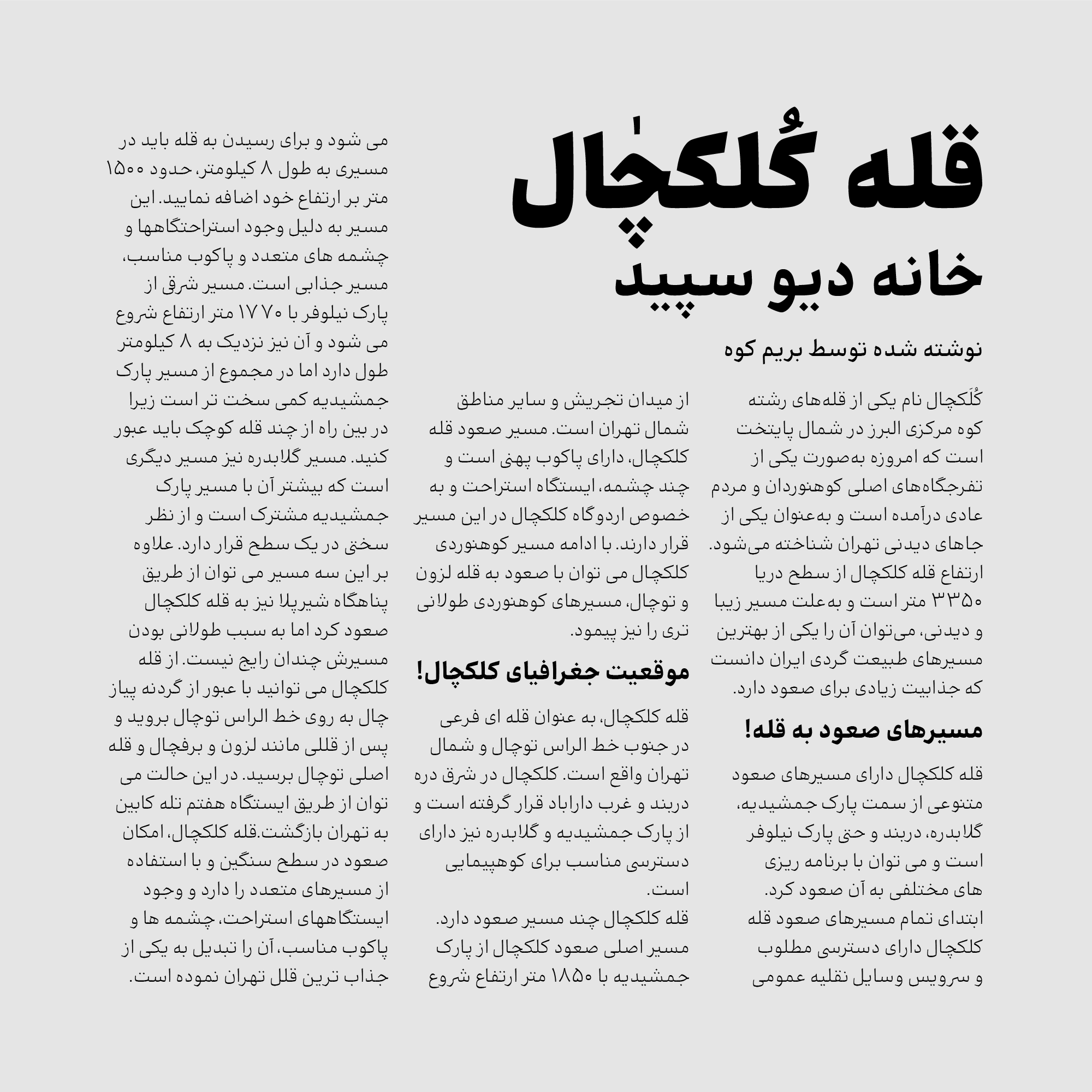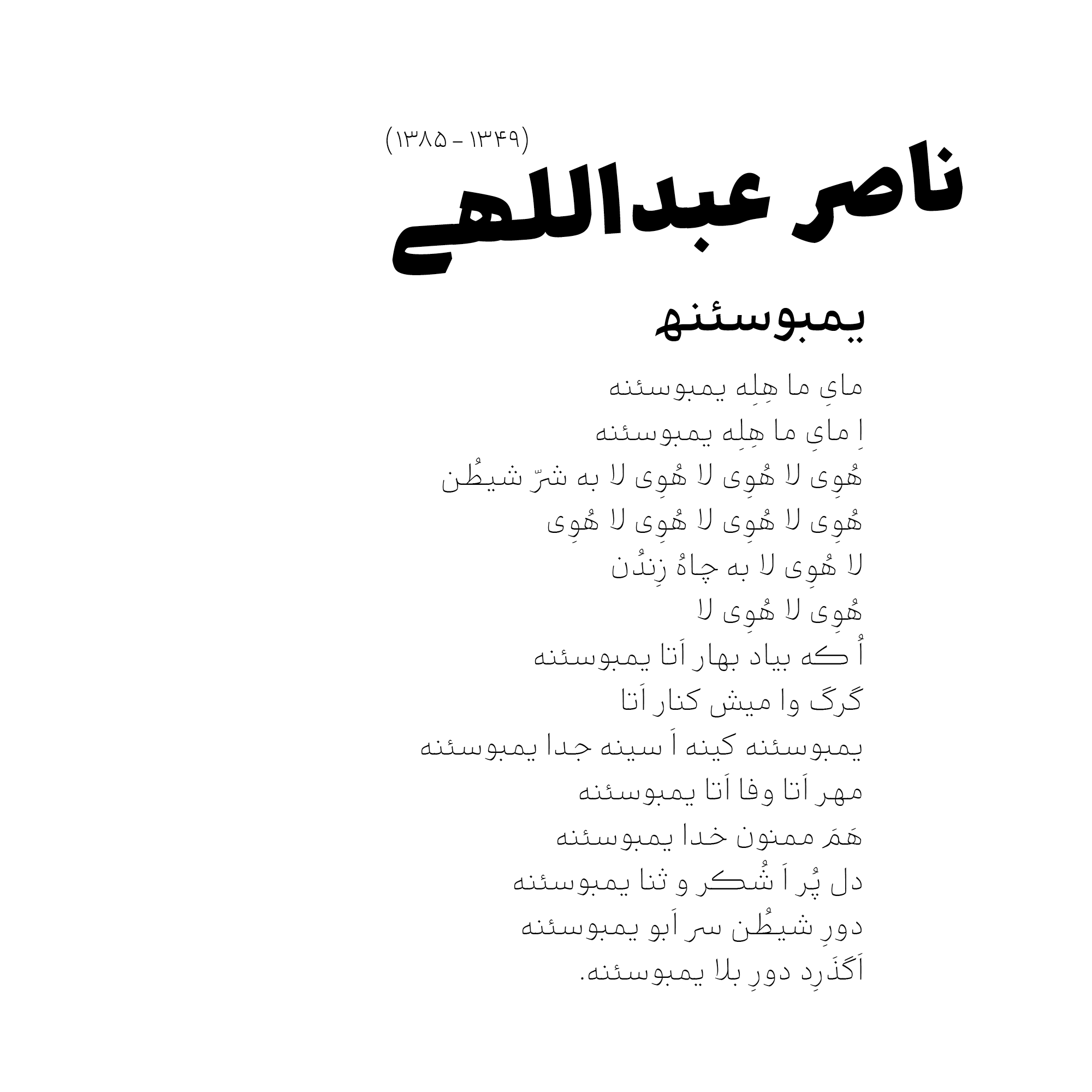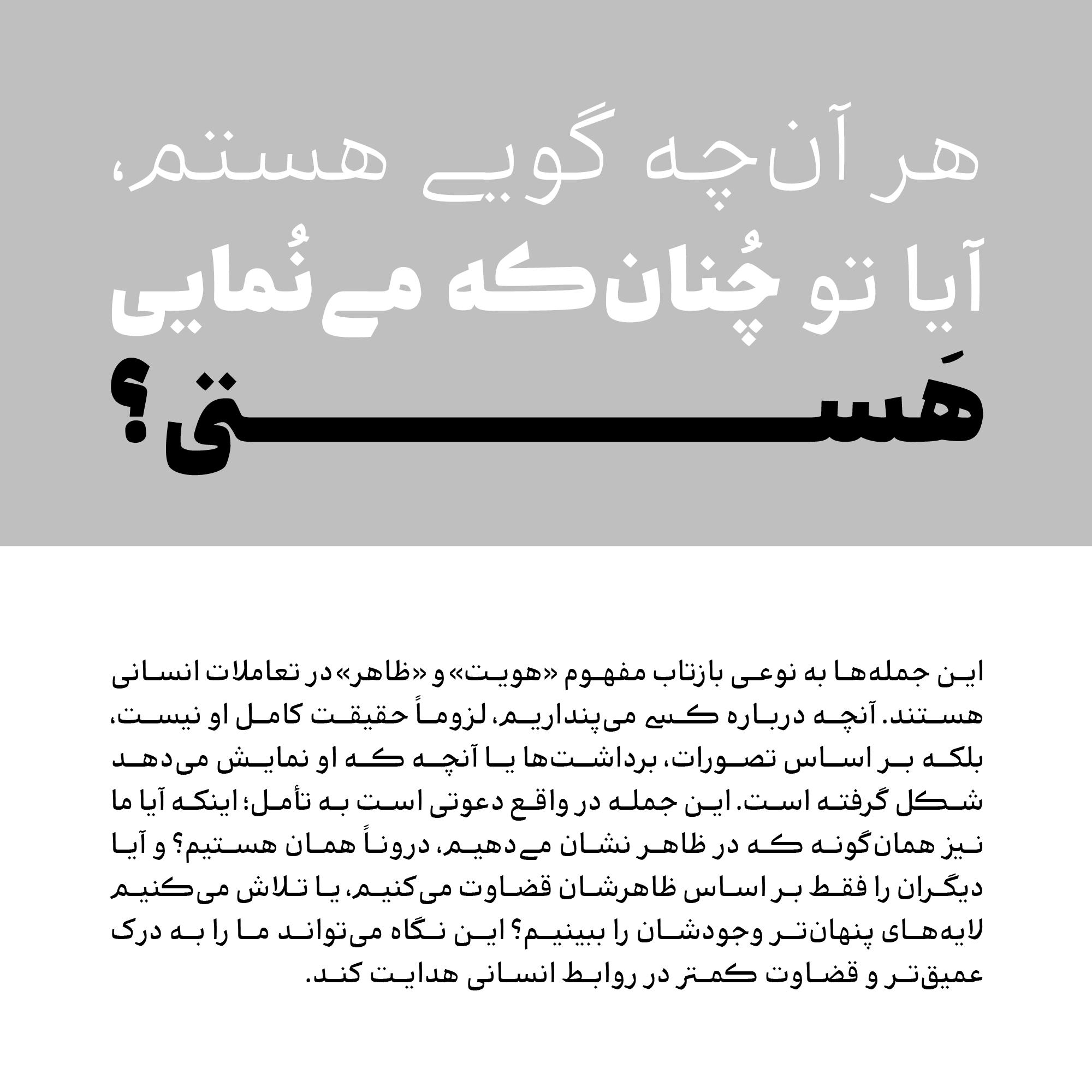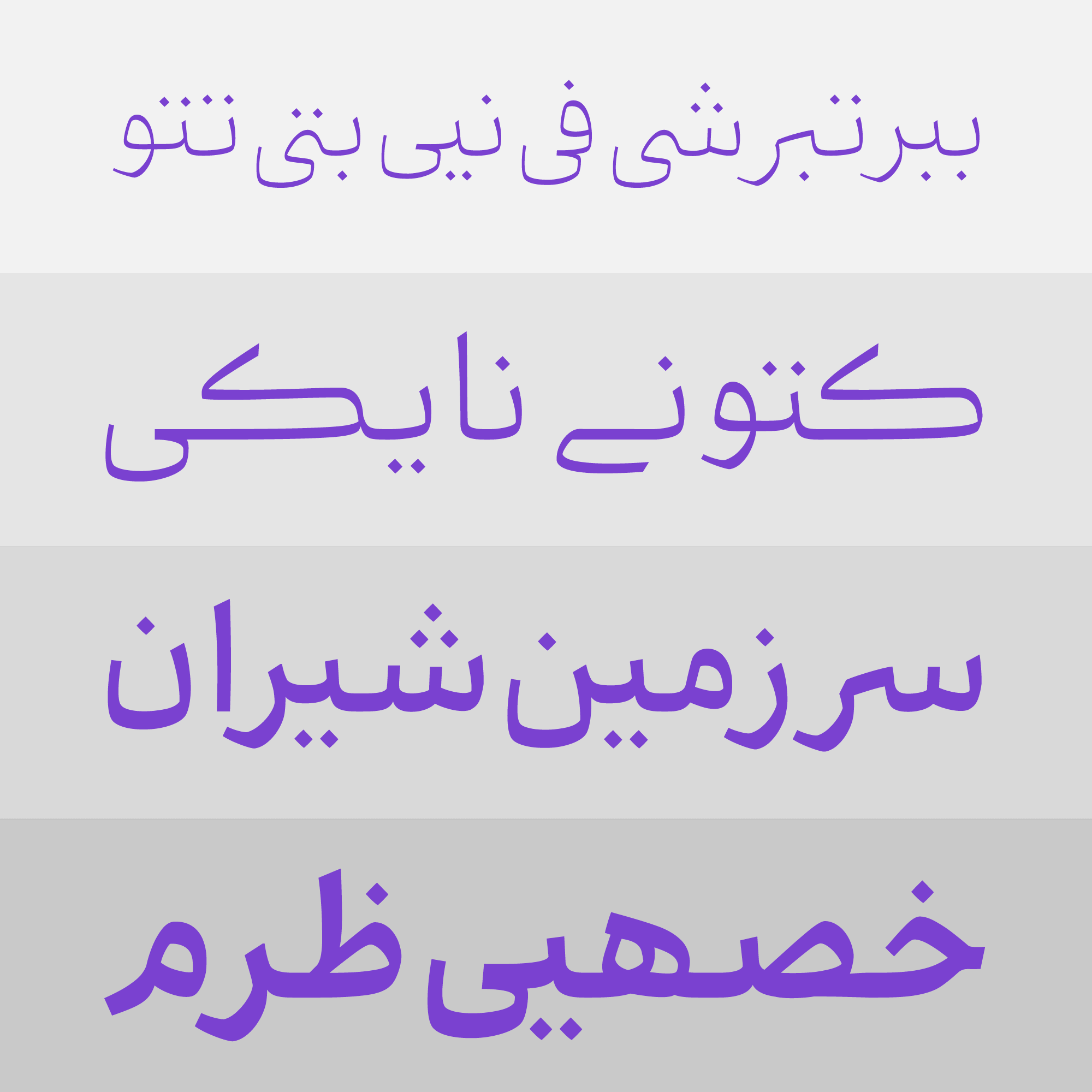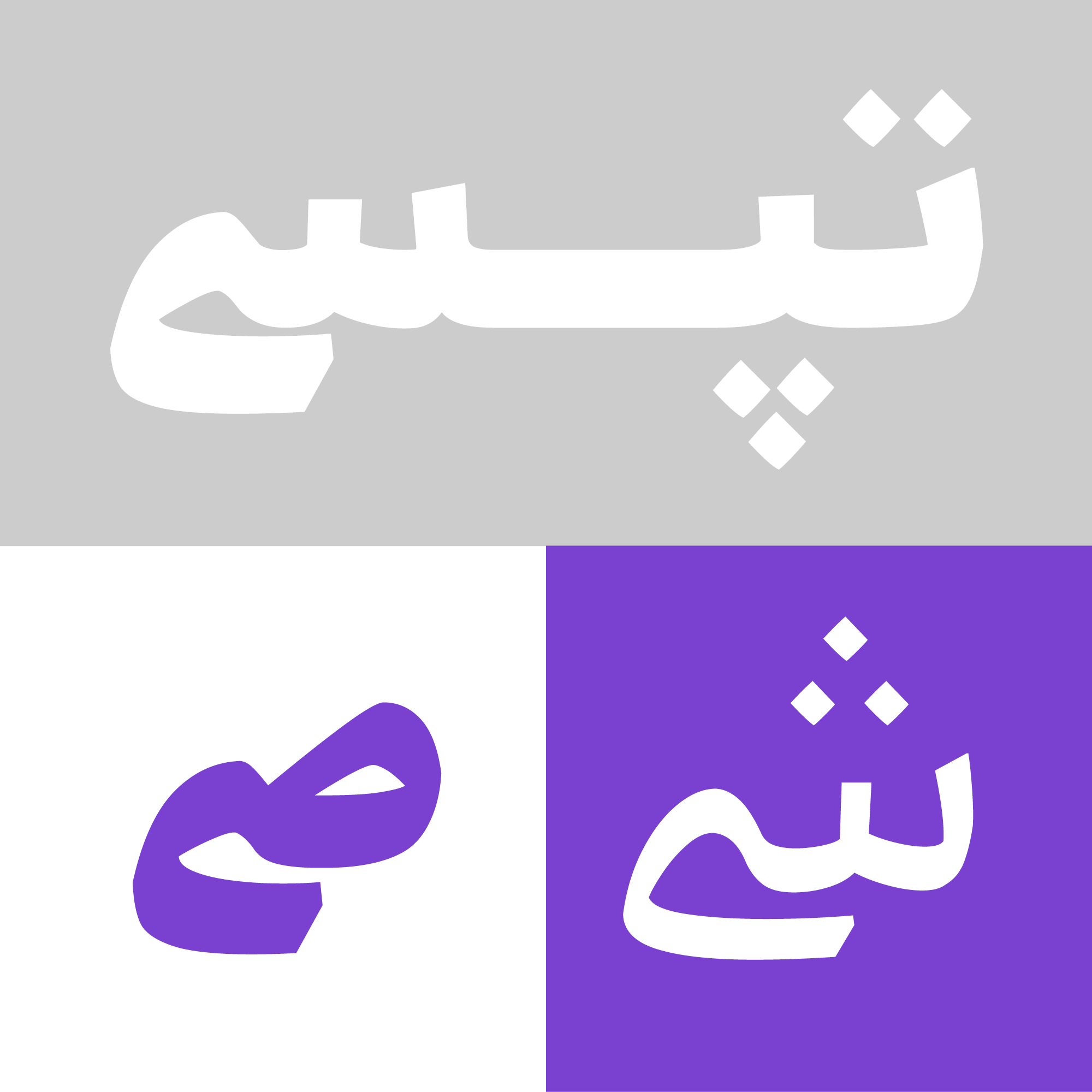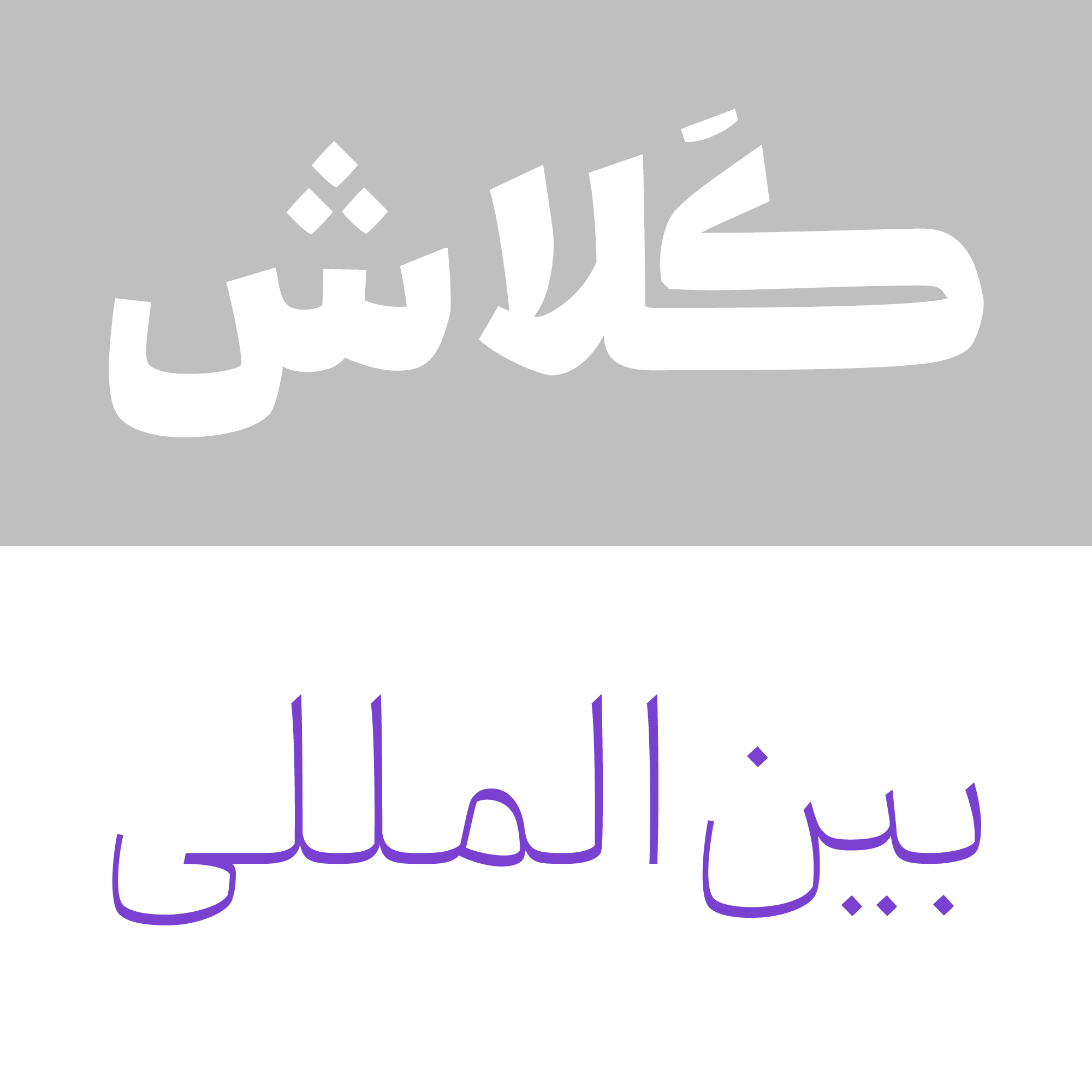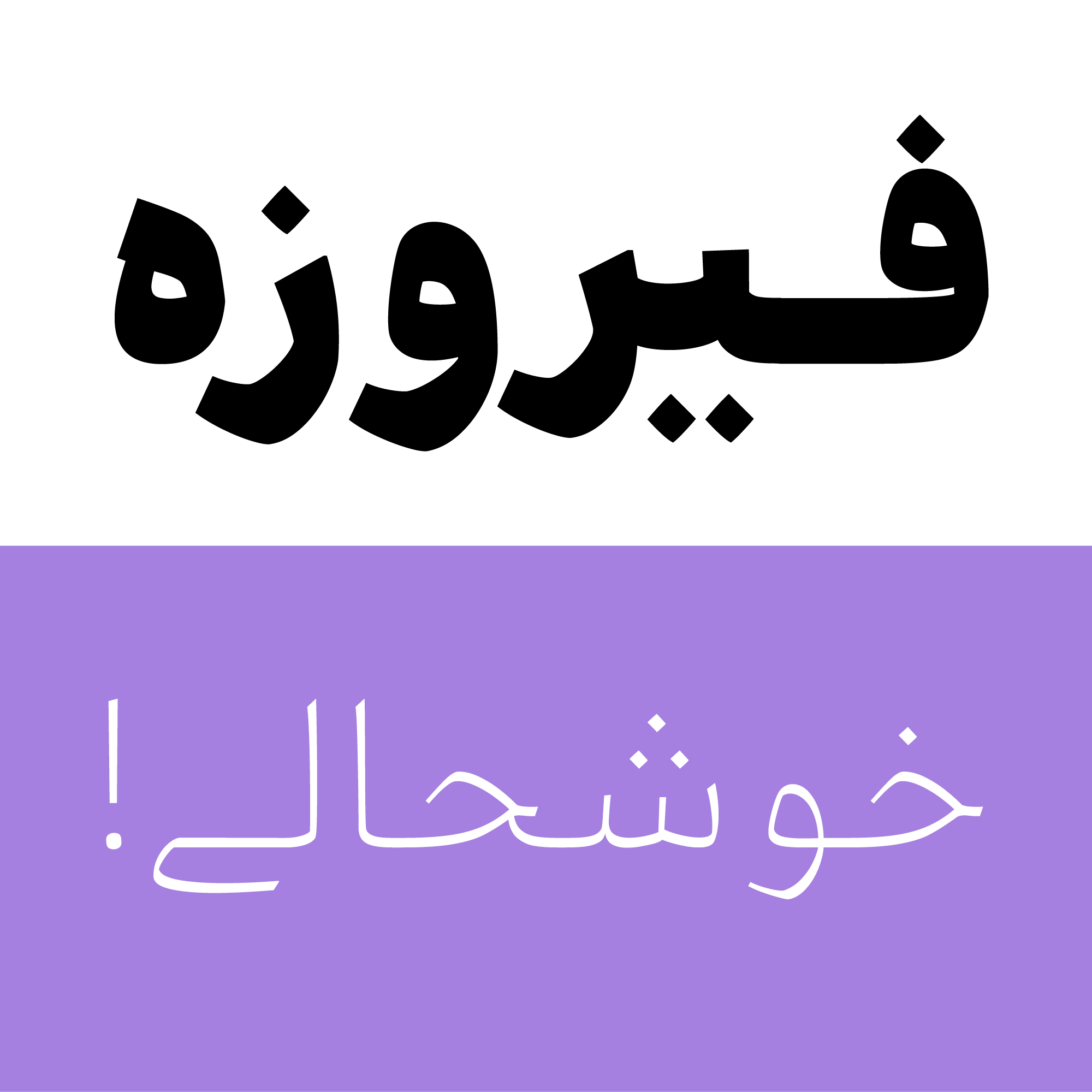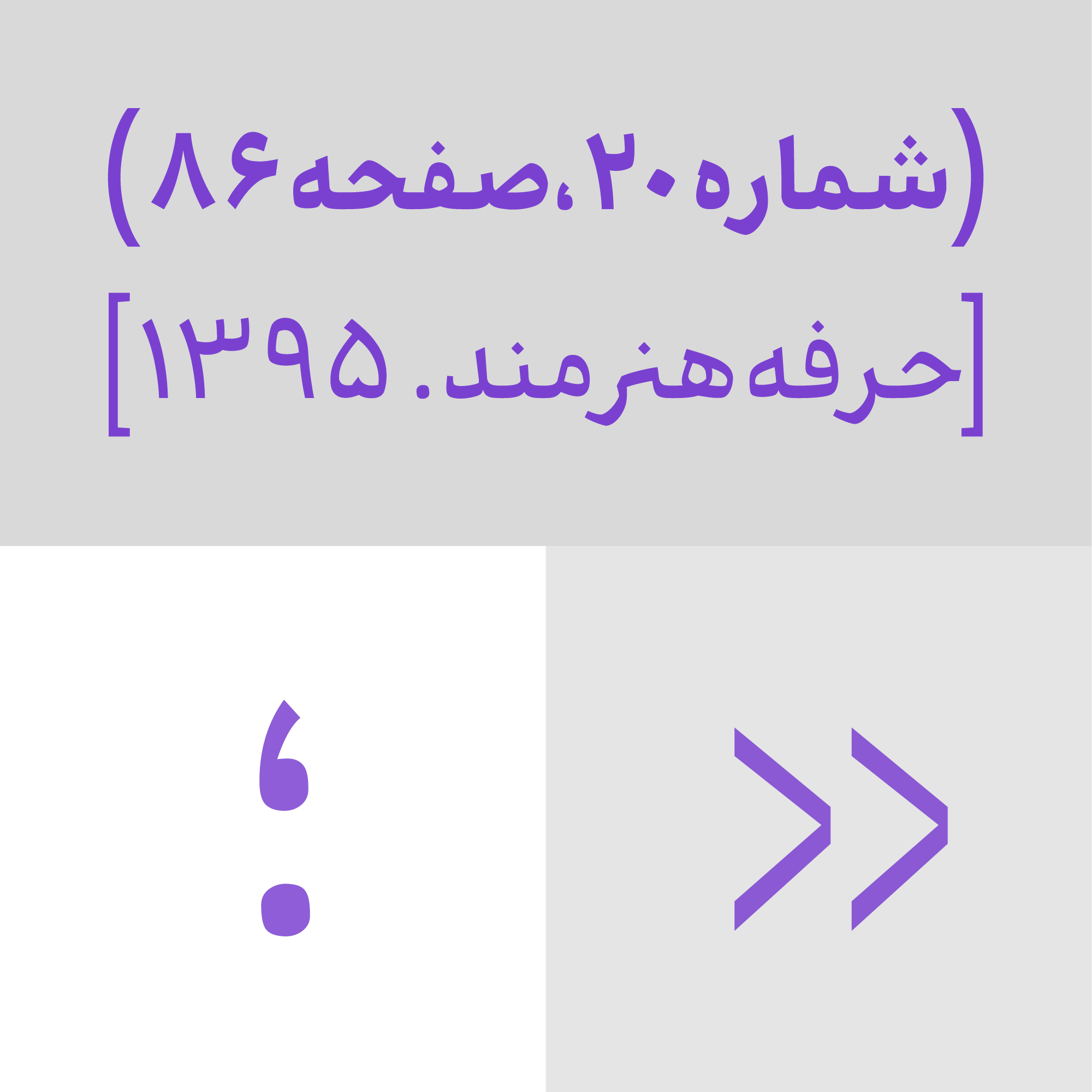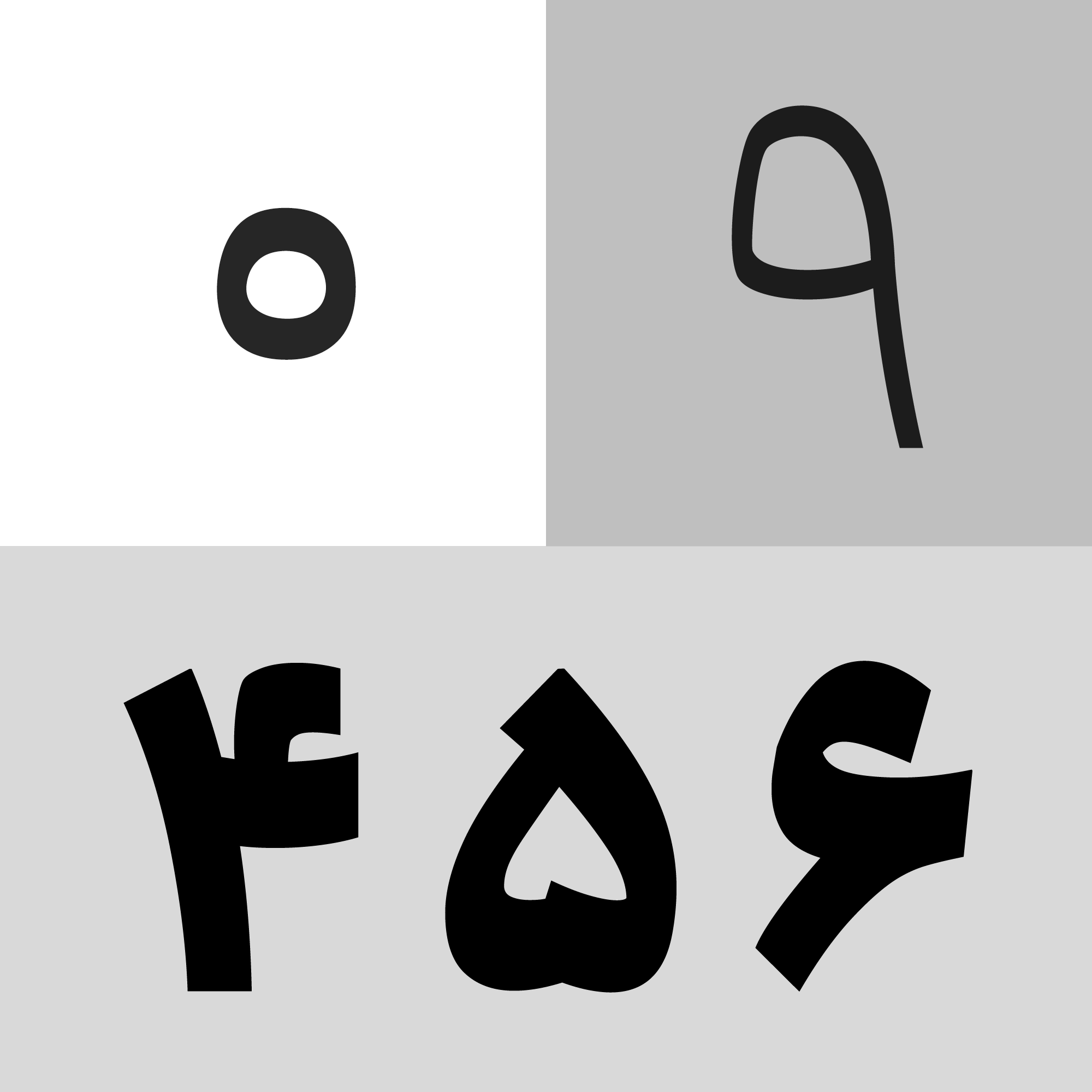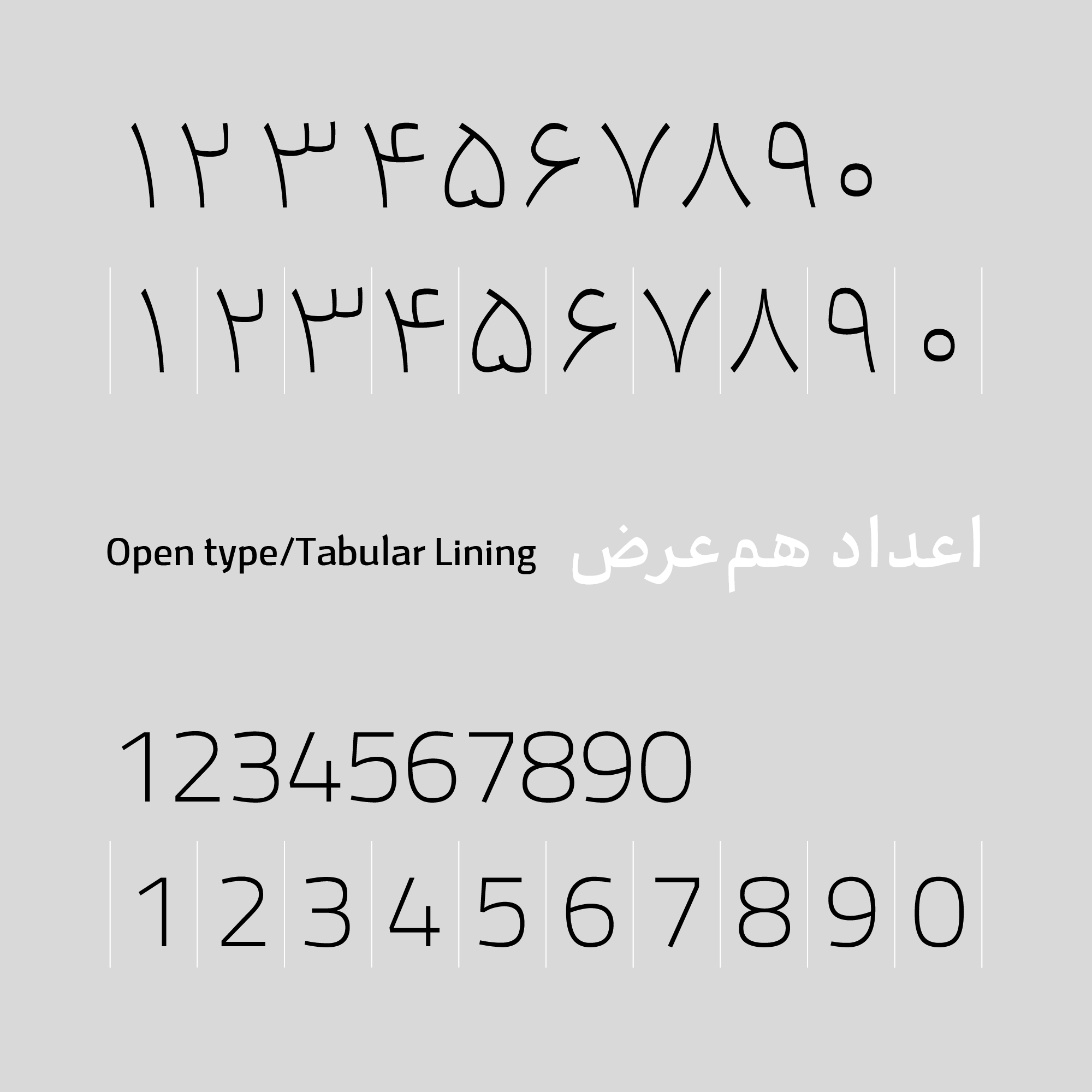
امکانات حروف مرکب(لیگاچرها) و حروف جایگزین (آلترنتیو): برای تایپوگرافی متفاوت کاراکترهایی چون کاف کشیده، میم کوتاه و شمارگان همعرض ویژگیهای دیگری هستند که با فعال کردن گزینه مخصوص آنها در قسمت open type نرمافزارها، امکان تغییر و دسترسی برای شما فراهم میشود.
پشتیبانی کامل از ۹ زبان مختلف رسم الخط عربی: «آنِ» جدید بهطور کامل از زبانهای متنوع پشتو، ترکی، تاجیکی، کٲشُری، قیرعیزی، اویغوری و دیگر زبانها پشتیبانی میکند. این ویژگی باعث میشود فونت «آن» برای استفاده در متنهای دوزبانه و چندزبانه مناسبتر باشد.
از دیگر نکات ویژهٔ فونت آن، برای هماهنگی بهتر در متنهای مختلف دو زبانه (Multi-Script) حروف لاتین هم طراحی شده.
در نسخه جدید همانطور که مشاهده کردید تغییرات چشمگیری در ساختار کاراکترها انجام شده. پیشنهاد میشود مقایسههای پایین را ببینید.
- اصلاح فرمها و منحنیها: با افزایش منحنیها و بهبود سطوح دوایر، فونت جدید «آن» نرمتر و لطیفتر از نسخه قبلی شده است و به همین دلیل دارای تعادل بیشتر و هارمونی بهتر است.
- بهبود کنتراست ضخامتها: یکی از ویژگیهای مهم این بازآفرینی، تغییرات اساسی در کنتراست ضخامت حروف است. در نسخه جدید، تناسب وزنها از سبک نازک تا ضخیم بهطور مؤثری متعادل شدهاند. بهویژه در وزنهای سیاه و ضخیم، فرمهای حروف کاملا تغییر کردهاند و بهبود قابلتوجهی در تشخیص و انسجام کلی فونت ایجاد شده است.
- بهبود فضای سفید حفرهها: حجم فضای سفید حفرهها بهطور معناداری اصلاح شدهاند. این تغییرات موجب بهبود وضوح حروف در اندازههای مختلف شده و باعث میشود که متنها یکدست و دلپذیرتر به نظر برسند.
- طراحی هماهنگ با حروف لاتین: در نسخه قبلی از یک فونت لاتین برای هماهنگی با حروف فارسی استفاده شده بود اما برای «آن» جدید، حروف لاتین مختص به خودش طراحی شده تا هماهنگی و یکپارچگی بیشتری در متنهای مختلف با حروف فارسی داشته باشه.
و در پایان: نسخه جدید فونت «آن» با اصلاحات و بازآفرینی دقیق و هدفمند، روحیهای رسمی و هویتی یکپارچه پیدا کرده است. این تغییرات باعث ارتقاء عملکرد فونت شده و بهطور کلی «آن» در ارائه تجربه بصری و کاربری باکیفیتتر، کاربردپذیری مؤثرتر و زیباتر به طراحان و کاربران فونت کمک میکند تا جنبههای مختلفی از نوشتار فارسی ارائه دهد.